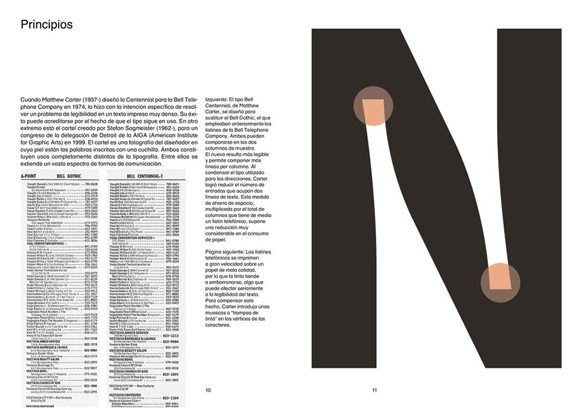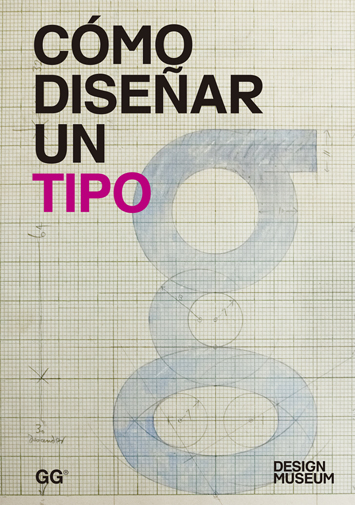
La Editorial Gustavo Gili presenta una nueva colección Design Museum dedicada a la divulgación de la cultura del diseño y lo hace con tres títulos: Cómo diseñar una lámpara, Cómo diseñar una silla y Cómo diseñar un tipo. Esta colección viene avalada por el Design Museum de Londres uno de los principales museos dedicados al diseño contemporáneo en todas sus formas de expresión y promete unos contenidos didácticos, concisos y agradablemente ilustrados.
Quiero pensar que vosotros ya os imagináis que título de los tres vamos a comentar en estas líneas. Y precisamente lo primero que me gustaría comentar es el título y es que si lees en la portada Cómo diseñar un tipo te puedes llevar la impresión de que en sus páginas encontrarás, más o menos detallados, los elementos y procesos que conducen a la realización de una tipografía, y esto no es lo que vamos a encontrar en los contenidos de este libro. Para los que están interesados en estos contenidos os voy a recomendar otro título de la editorial: Diseñar tipografía de Karen Cheng
Una vez aclarado esto, vamos a repasar los contenidos del libro. Como siempre hemos defendido en unostiposduros, la tipografía es “hija de su tiempo”, cualquier diseño tipográfico comparte una época, un contexto sociocultural que acaba forjando una expresión gráfica . El conocimiento de las diferentes etapas por las que ha transcurrido y transcurre el diseño tipográfico nos proporciona una valiosa información que podemos utilizar en nuestras actuales tipografías digitales.
Desde esta premisa es desde donde podemos comenzar a hablar de los contenidos de Cómo diseñar un tipo. El libro consta de dos partes básicas una de tipo técnico y cultural englobada en los capítulos “Principios” y “Procesos” y otra de corte más práctico, una entrevista al diseñador tipográfico Jonathan Barnbrook. En el capítulo “Principios” encontramos información general acerca del dibujo de las letras y su facilidad para ser leídas, aspectos connotativos de sus formas y como estas se articulan en un texto. Se trata de comprender las funciones principales de la tipografía, esto es, transmitir una información sobre un soporte determinado sin olvidar el concepto o imagen que las mismas letras portan en sus formas y teniendo en cuenta la facilidad de comprensión del mismo por parte del lector.
El objetivo de esta parte del libro es dejar claro las premisas básicas que debemos perseguir a la hora de diseñar o utilizar una tipografía y sobre los que se sustentan una parte importante de su utilidad en un trabajo de comunicación: legibilidad, imagen y lecturabilidad. Por otro lado en el capítulo titulado “Procesos” asistimos a un paseo por los estilos tipográficos aparecidos a lo largo del tiempo. Se trata de un paseo largo ya que comienza en el siglo XV con la tipografía de plomo y finaliza en los diseños digitales contemporáneos.
Partiendo de la aparición de la escritura y los primeros alfabetos, y con un texto ágil acompañado por unas ilustraciones y fotografías muy bien escogidas, el lector puede asistir al nacimiento de la composición tipográfica de la mano de Gutenberg y sus pesados tipos góticos, la aparición del Renacimiento y su ligera letra humanista, las letras de la era de la razón protagonizada por Baskerville, las letras románticas de Bodoni y la eclosión de la mecanización de la imprenta en el siglo XIX con el advenimiento de la “composición mecánica”, las prensas de vapor y las tipografías de formas caprichosas. Tras esta primera etapa del desarrollo de la tipografía la aparición del movimiento moderno, interpretado por las vanguardias artísticas de principios del siglo XX y su búsqueda de la racionalidad y la función, también encuentra acomodo en las páginas del capítulo y su hilo conductor nos dirige, pasando por el diseño suizo, hasta las posturas postmodernistas implementadas dentro de una revolución digital propiciada por la aparición del ordenador personal.
En la segunda parte del libro una entrevista con el diseñador tipográfico Jonathan Barnbrook al hilo de una creación suya, la tipografía Priori, nos permite conocer de primera mano las ideas en torno a la tipografía, su función y su creación que maneja un diseñador de tipos al mismo tiempo que nos habla de los procesos implicados en su realización.
Finaliza el libro con un útil índice alfabético y un pequeño glosario de términos relativos a la materia tratada.
En fin, cómo hemos señalado al inicio de esta recensión, con este libro no vamos a aprender o conocer los procesos implicados en el diseño de una tipografía, desde su boceto inicial a las características de sus formas, ajustes ópticos, espaciado, kerning, etc. Por el contrario lo que si vamos a obtener es una visión ágil y muy bien ilustrada del desarrollo de la tipografía a través del tiempo contada de manera eficaz y amena.
Contenidos que os puedo asegurar son básicos y se configuran como una excelente “puerta de entrada” si queremos conocer a fondo los recursos que la tipografía nos proporciona.
Asimismo tenemos que señalar que la entrevista a Barnbrook nos ofrece unas muy buenas “pistas” sobre el diseño de tipos y sobre la actitud de un diseñador actual. Una información muy útil y práctica que unida a la visión global de la primera parte del libro, hacen de este título una pieza muy aconsejable de cualquier profesional o interesado en la comunicación.
Cómo diseñar un tipo
Colección Design Museum